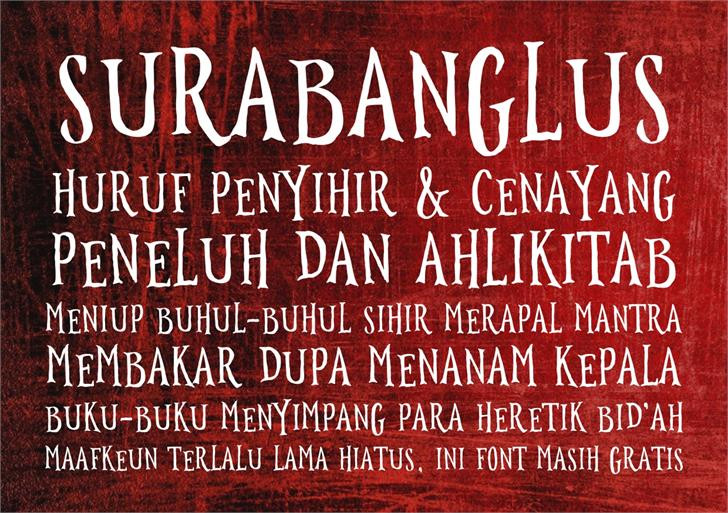
Surabanglus Font
Surabanglus-Font — By Gunarta
Surabanglus diambil dari judul salah satu cerita pendek Ahmad Tohari dalam bukunya “Senyum Karyamin”. Surabanglus sendiri adalah nama dari sejenis ketela yang beracun jika dimakan.
Surabanglus taken from the title of a short story Ahmad Tohari in his book ” Smile Karyamin ” . Surabanglus itself is the name of a type of yam which is toxic if eaten .